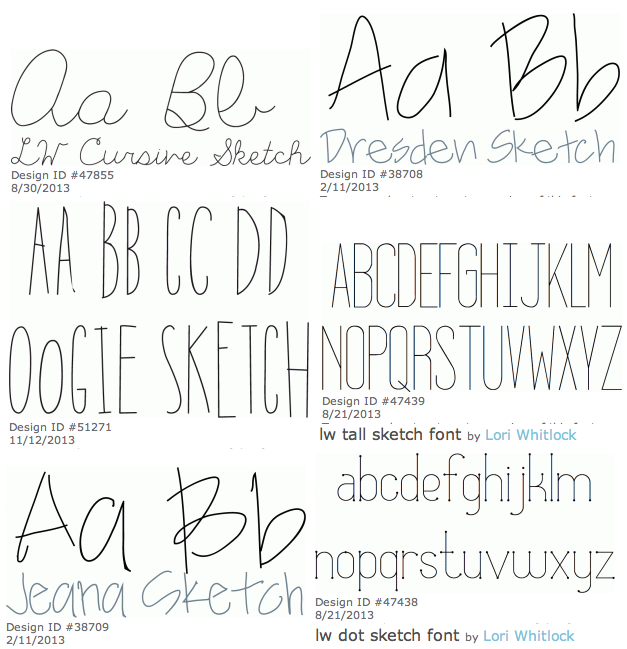
Все любят уникальные и креативные шрифты. Все, кроме тех, кто не имеет возможности их использовать. Чтобы решить проблему, вам необходимо установить подобные шрифты из директории Google Fonts.
Sketch- стиль Шрифты — CoderLessons.com
Здесь я собрал некоторые ресурсы, которые могут оказаться полезными, если вы заинтересованы в применении популярного стиля эскиза к вашим собственным проектам.
Вот подборка шрифтов, кистей и векторов Photoshop, которые были нарисованы, нарисованы от руки и нарисованы.
Ноты Казуары, Нормальная Альбертина Невана
Тиза Пабло Каро
Tusj (тушь) от Магнуса Седерхольма (formfett.net)
Блок эскизов от Лукаса Бишоффа
Sketchy Times by! Exclamachine Type Foundry
Зеленая подушка от Билли Арджел
Денн Тридее от Дениз Бентулан
Атман Дингбат от Eyesaw
Че Вива Банан от Font Environment. На их сайте также есть много дингбатов в стиле отрывочников.
Есть, конечно, гораздо больше схематичных шрифтов. Вот отрывочные и нарисованные от руки стили на dafont .
Никого наверное не удивит тот факт, что выбрать тему для диплома не просто и выбор этот глубоко индивидуален для каждого. Но почему же Химера? Почему же такой «странный» шрифт? Почему не (о боже!) текстовый шрифт? Почему без кириллицы? Я постараюсь расставить точки над i. Как бы оно не было странно на первый взгляд, на меня активно повлияла предыдущая большая работа — Все шрифтовые проекты, над которыми мне удалось поработать, также фактически сводились к добавлению кириллицы к существующему усредненному (проще говоря «никакому») латинскому аналогу. Такая работа мне вначале была интересна как опыт, с чисто технической стороны, когда я её делала в первый раз, но впоследствии я впадала в ещё большую тоску. Мне хотелось эсперимента, но я не знала с чего начать. Я часто видела реакцию «обывателей» на текстовый шрифт: «Разве таких ещё не существовало?!», «Чем же он отличается от других?». Такая реакция абсолютно нормальна.. но подсознательно мне хотелось противопоставить ей что-то координально отличающееся, разработать шрифт, который выглядел бы новым, уникальным даже для не разбирающегося в шрифтах человека. Продолжая работать и получая опыт работы с российскими заказчиками я понимала, что нереально будет получить шрифтовой проект, позволивший бы мне развиваться и экспериментировать. И так как мне не хотелось потерять всякий интерес к профессии, я решила сделать всё возможное, чтобы поступить в KABK и посвятить год работе над собой в Гааге, на курсе который развивает как технические, так и разнообразные практические навыки. Кроме наличия безусловного характера, моей сверхзадачей при выборе темы диплома стало не фокусироваться на кириллице. В сфере кириллических гарнитур из-за общего их малого количества по сути что ни сделай, всё будет кстати. А вот поконкурировать в сфере латинницы… где казалось бы всё возможное уже сделано… Химера, кажущаяся, смотря на первые эскизы, абсолютно нежизнеспособной идеей, привлекла меня именно невозможностью спрогнозировать результат. Меня безумно влекло то, что я от начала до конца работы не была уверена в состоятельности проекта. Эти ощущения добавляли азарта и стремления сделать всё возможное для его осуществления. Первые эскизы и первые пробы оцифровки эскизов прямого начертания Были люди, которые меня поддерживали, не давали расслабляться и подталкивали развивать идею. В первую очередь это Эрик ван Блокланд (Erik van Blokland).
Скетч. Шрифт. Процесс. Химера.